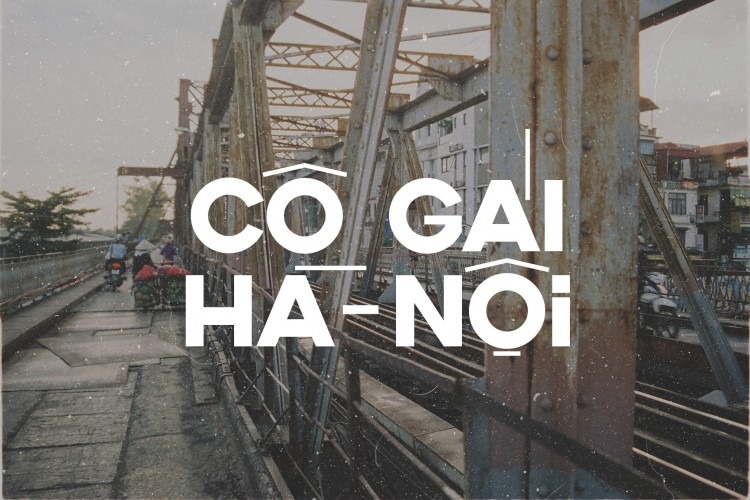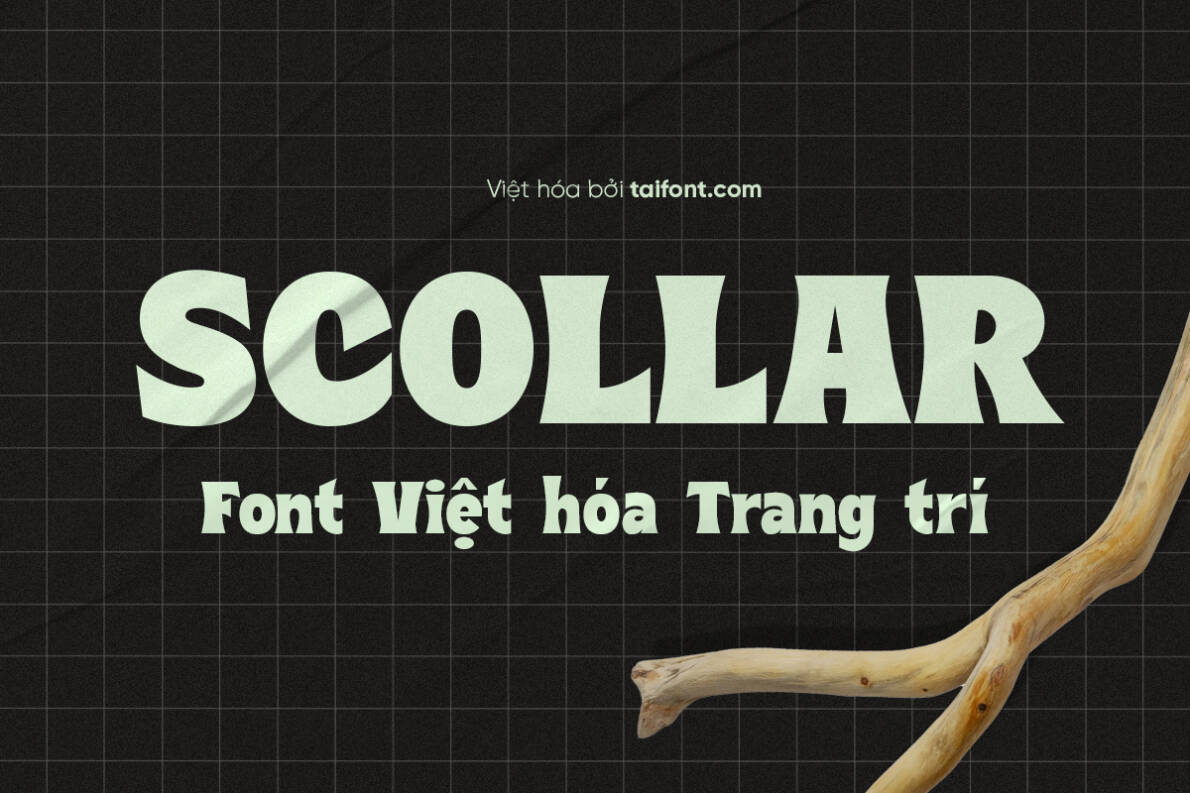
Font chữ PowerPoint tiếng Việt đẹp
Font chữ PowerPoint tiếng Việt đẹp, dùng cho thiết kế thuyết trình slide, làm tiêu đề banner bài giảng
Font Việt hóa TF Scollar | Link tải
Font Việt hóa iCielBC Cubano | Link tải
Font Việt hóa iCielBC Cubano là một font chữ được yêu thích sử dụng tại Việt Nam bởi nét đẹp của nó.
Cubano thuộc dạng font Vintage, không chân có đặc điểm nét đậm. Font phù hợp đang dạng sử dụng trong thiết kế quảng cáo, slide thuyết trình.
Font Cubano được dùng rất nhiều trong thiết kế ấn phẩm truyền thông.
Font Việt hóa Bungee | Link tải
Font Việt hóa Bungee là một font chữ được chia sẻ trên Google font. Font có nét đậm và chắc chắn.
Đối với font chữ Bungee bạn có thể dùng nó để thiết kế các biển quảng cáo, biển báo thông tin. Với đường nét đậm có thể quan sát thấy nội dung từ xa.
Font do tác giả David Jonathan Ross và thuộc nhóm font Trang trí.
Font Việt hoá L’Hanoienne Typeface | Link tải
Font Việt hoá L’Hanoienne Type face là một font chữ không chân gây ấn tượng mạnh mẽ đối với bất kì ai nhìn thấy nó.
Nó phù hợp với các thiết kếẩm thực, dùng cho tiêu đề, cho các banner mang xu hướng cổ.
Font Việt hóa TF TAN – KINDRED | Link tải
Font Việt hóa TF TAN – KINDRED là một phông chữ hiển thị tương phản quang học có bản chất tinh nghịch và vui nhộn